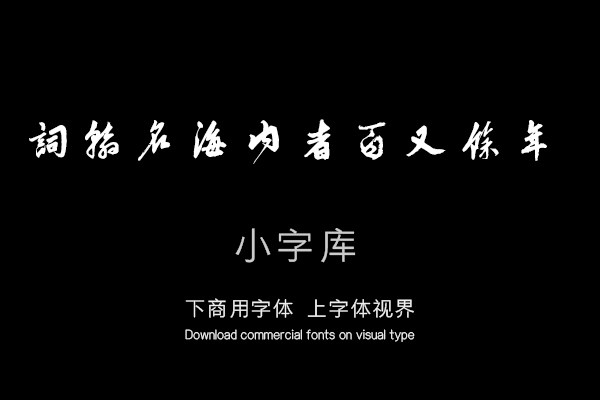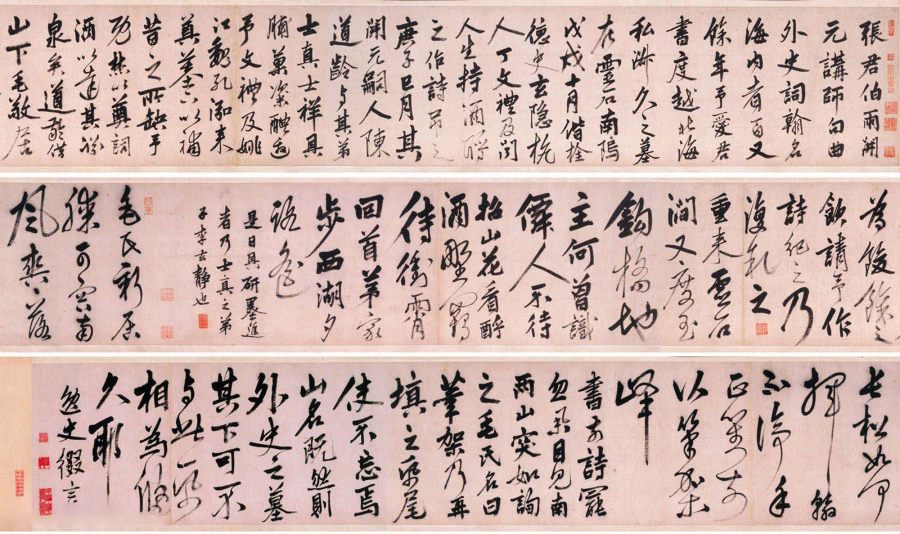
《汉标姚绶拜张伯雨墓诗》是一款根据明代姚绶经典行书作品拜张伯雨墓诗卷,经过再次调整制作的小字库,该小字库共收录了该真迹作品中约338个字体。单字授权
张君伯雨,开元讲师,句曲外史,词翰名海内者百又余年。予爱君书,度越北海,私淑久之。墓在灵石南隖,戊戌十月偕栓德、史玄隐、杭人丁文礼及闻人生,持酒酹之,作诗吊之。庚子巳月,其开元嗣人陈道龄,与其弟士真、士祥,具脯菜粢醴,邀予、文礼及姚江魏孔泓来奠墓下,以补昔之所缺。予既焚以奠,词酒以达其渊泉矣。道龄借山下毛敬居为饯余之饮,请予作诗纪之,乃复叙之。 重来灵石涧,又度玉钩桥。地主何曾识,倦人不待招。山花看酹酒,野鹤待冲霄。回首茅家步,西湖夕路遥。是日具研墨进者,乃士真之弟子李玄静也。毛氏新居膝可容,南风爽爽落长松。如何挥翰不停手,正对前山笔架峰。书前诗罢,忽举目见南两山突如。询之毛氏,名曰笔架。乃再填之纸尾,使不忘焉。山名既然,则外史之墓其下,可不与此纸相为悠久耶。逸史缀言。